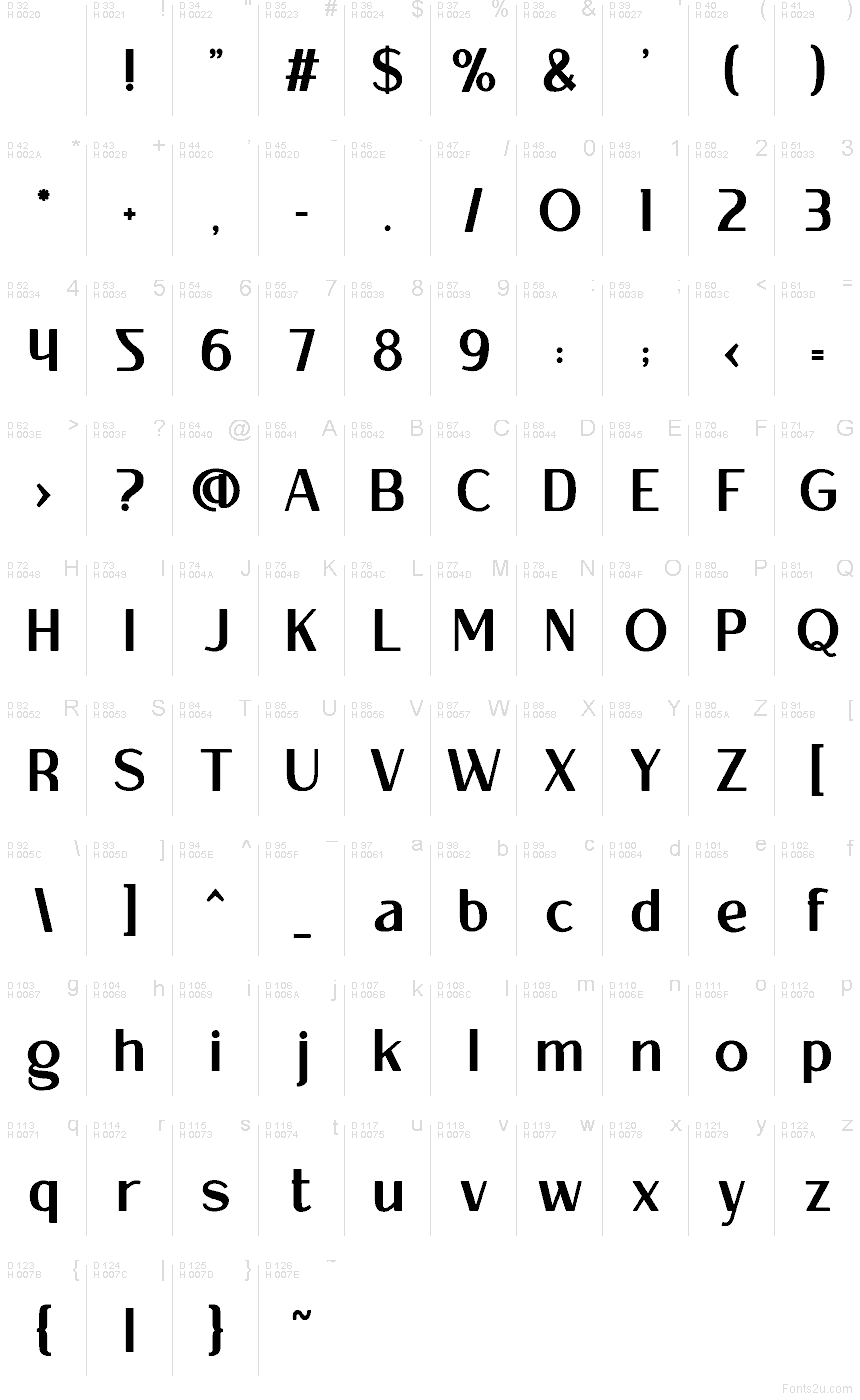
Savenir Sans
Savenir Sans od Putracetol Studio je bezplatné bezpätkové písmo s pokojným, vzpriameným rytmom a jemne sa zužujúcimi ťahmi, vďaka ktorým pôsobia písmená hladko a nie stroho. Toto ľahké zúženie v spojoch dodáva dizajnu až kaligrafický nádych, takže pôsobí rafinovanejšie a literárnejšie než bežné bezpätkové písmo.
Skvele sa hodí na obálky kníh, redakčné nadpisy, branding butikov, obaly a plagáty, kde tichá silueta stále dokáže upútať pozornosť. Zaoblená konštrukcia a vyvážený rytmus dodávajú krátkym textom prirodzený vzhľad, či už ide o etikety kozmetiky alebo jedálne lístky, najmä ak projekt vyžaduje jednoduchosť bezpätkového písma bez suchého geometrického tónu.